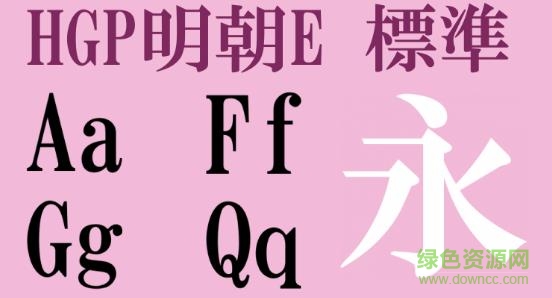
hgp明朝e字體是一款線條較粗的日文字體,結(jié)構(gòu)端莊,線條清晰,效果醒目,給人的感覺(jué)莊重大氣,可以用在期刊、報(bào)紙的的標(biāo)題處,喜歡的朋友快來(lái)下載吧!
宋體字名為宋體,其實(shí)誕生在明朝,而其根本原因是明清兩代文人仰慕宋朝文化、追捧宋刻本所致,日本的明朝體,是由于美國(guó)人姜?jiǎng)e利(William Gamble)于1859年將上海美華書(shū)館所制的六種字體傳入日本,并指導(dǎo)日人本木昌使用電鍍字模制造法所制成的字體